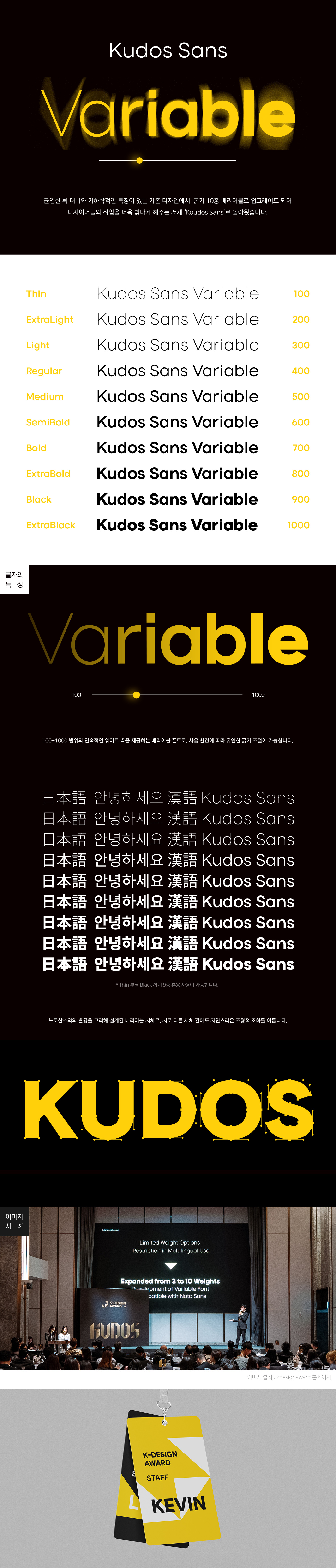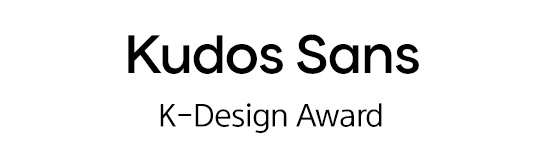
지오메트릭 기반의 고딕 영문 서체로, 균일한 획 대비로 안정감을 주며 정원에 가까운 원형과 기하학적 형태를 가지고 있습니다. 배리어블 폰트를 지원하며 노토산스와 자연스럽게 혼용해 사용할 수 있도록 제작된 서체입니다.
| 프로젝트명 | Kudos Sans |
| 스펙 | 영문 94자 / 라틴확장 223자 / 리가처 기호 6자 / 약물 83자 |